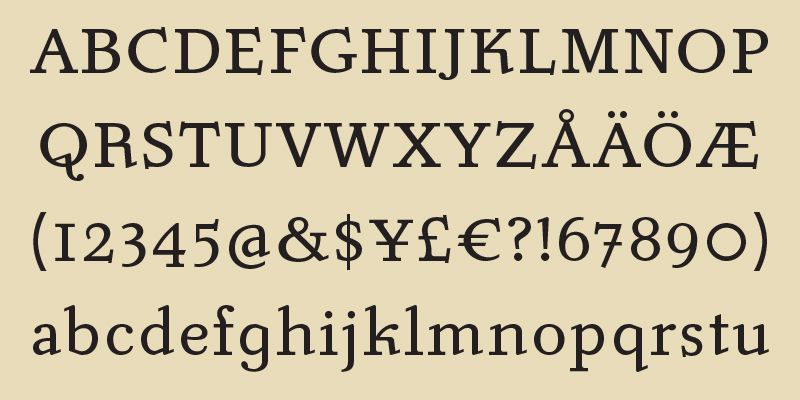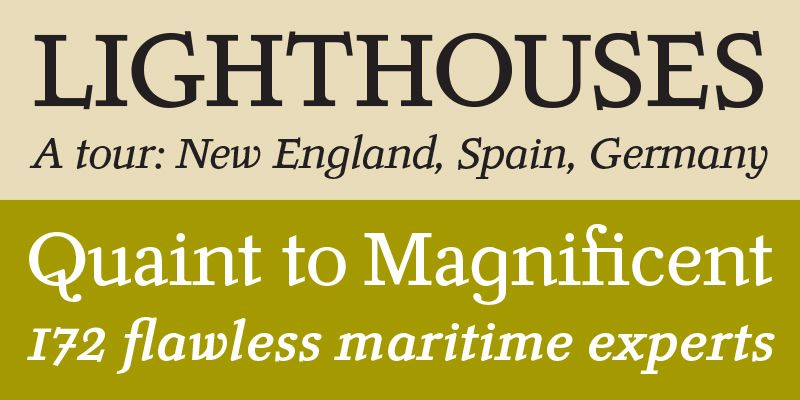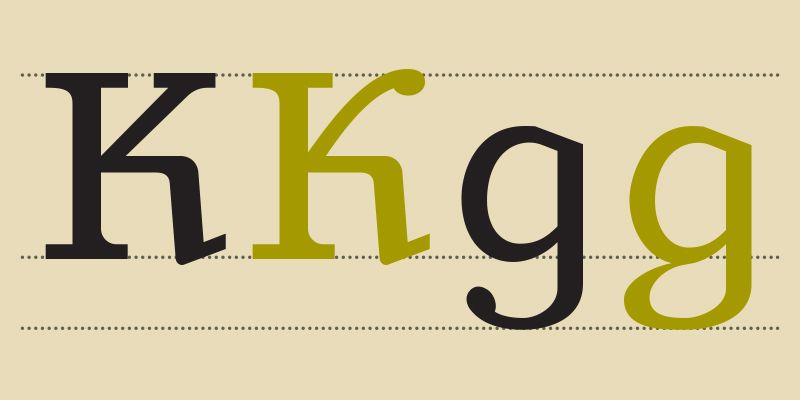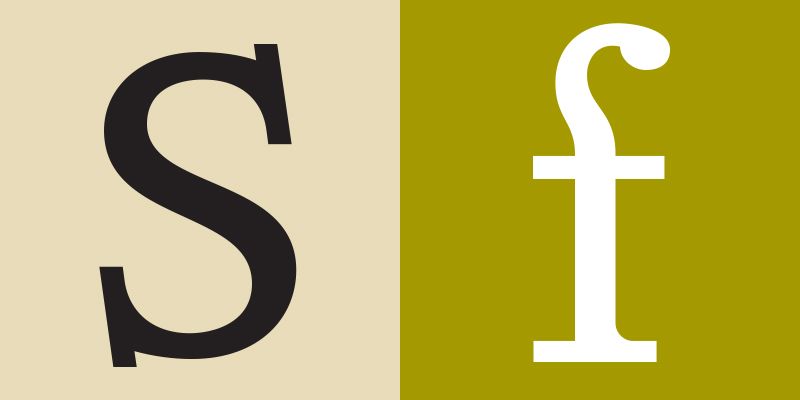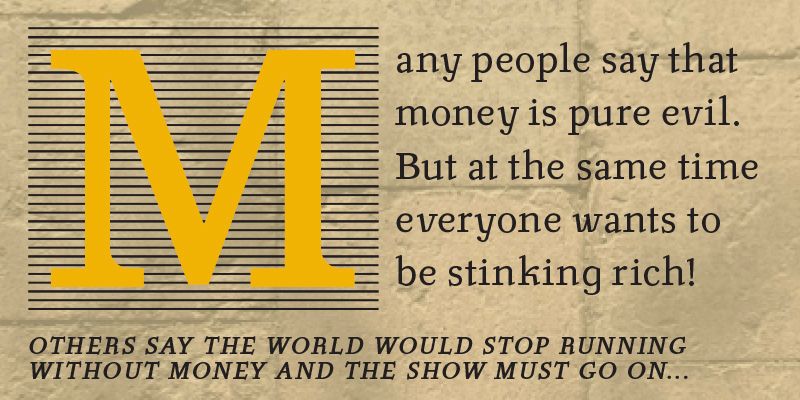
Ein Ergebnis der Faszination für osteuropäisches Schriftdesign. Inspiriert von der Schrift Pracht (von Carl Pracht in den Jahren 1941-43). Kann sowohl als Text- als auch als Display-Schrift verwendet werden.
Stefan Hattenbach ist ein renommierter schwedischer Schrift-Designer mit über 30 Jahren Erfahrung in Typografie, Grafik-Design und Werbung. 1980 begann er mit Werbung und 1994 wechselte er zum Grafik-Design. 1996 entwarf er seine erste Schrift und wurde Gründer von MAC Rhino Fonts. Hattenbach lebt und arbeitet in Stockholm, hat aber auch im Ausland in Budapest (1993–94) und San Francisco (2005–06) gearbeitet. Seit 2012 arbeitet er in Vollzeit an der Entwicklung von kundenspezifischen Schriften für inländische und internationale Unternehmen (bis 2018 mehr als 50 Schriften, darunter auch Sortimentsschriften). 2012/13 entwarf er zusammen mit der Designagentur Söderhavet die offiziellen Schriften für Schweden. Seine Sortimentsschriften sind seit der Veröffentlichung des ersten Designs New Global im Jahr 1996 auf der ganzen Welt verbreitet. Hattenbach pflegt eine große Leidenschaft für Buchstaben (enthusiastischer Sammler von Drucktypen). Er betrachtet Reisen als ein grundlegendes „Hobby“ und hat eine Schwäche für Italien. 100%iger Romanista (AS Rom-Fan) und Espressoliebhaber.